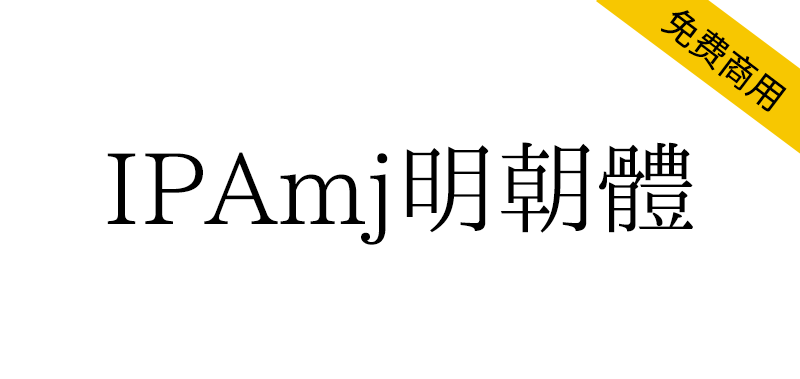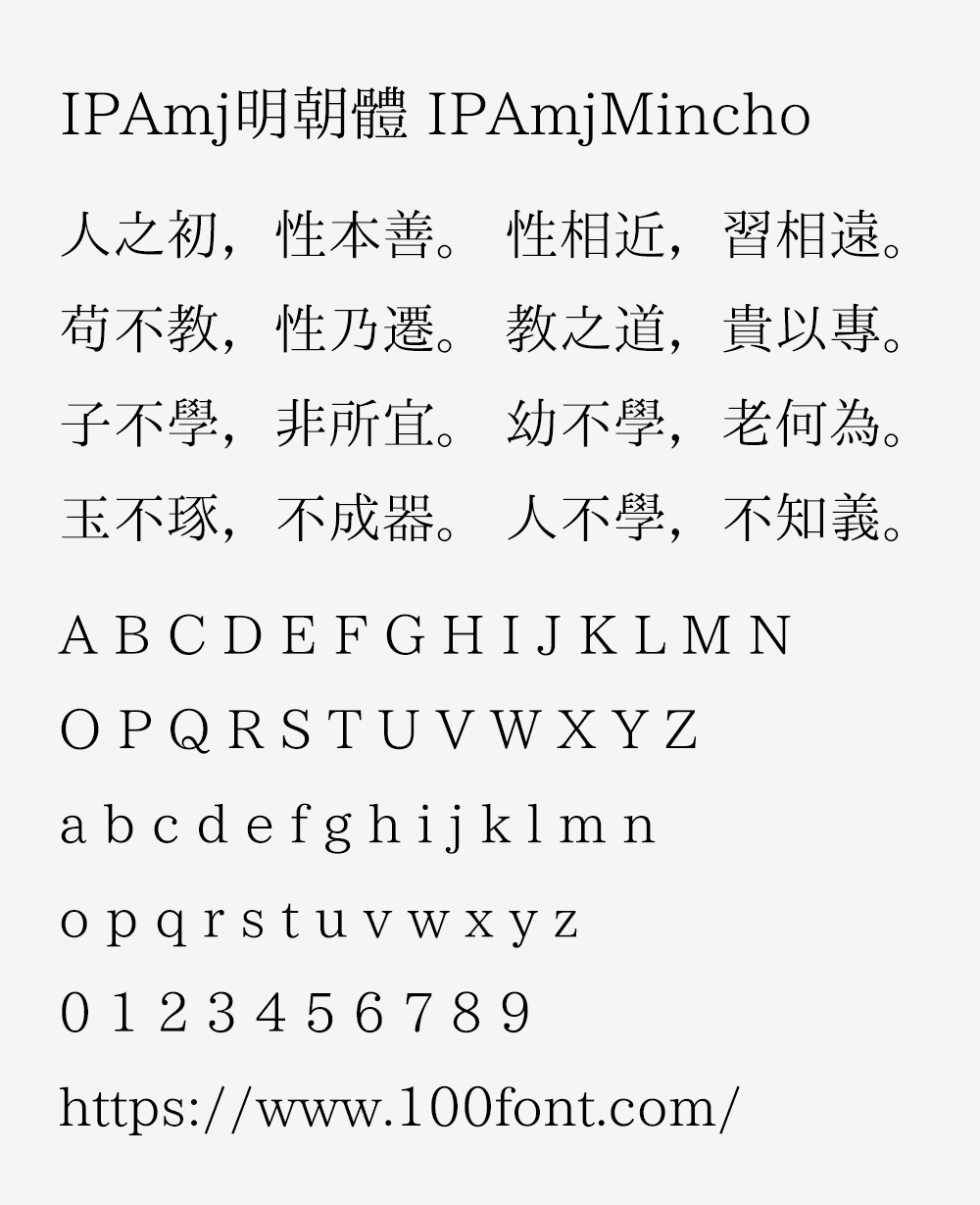
IPAmj明朝体(IPAmj明朝體 / IPAmjMincho)是日本IPA独立行政法人情报处理推进机构推出的一款字体,这是日本的一个关于文字信息基础建设事业的网站。IPA文字信息基础建设事业,是根据日本平成22年电子经济产业省推进计划(关于文字信息基础构建的研究开发事业)启动的,主要是对日本使用的约6万个汉字进行分类整理标准化项目。这个项目公开了《文字信息基础文字一览表》和《IPAmj明朝体》,是为了普及促进和国际标准化的活动。
「IPAmj明朝」是对「IPAex明朝」的进一步扩充,包含了「文字情报基盘」所涵盖的汉字及其诸多IVD 变体,IPAmj明朝体包含了更多的字符。